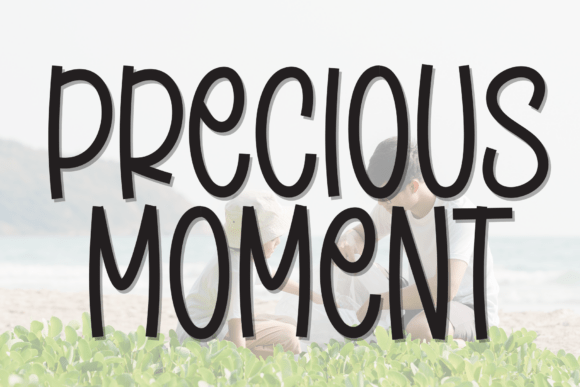
Precious Moment
قد يكون العثور على عناصر التصميم المناسبة أمرًا صعبًا، ولكن Precious Moment يقدم مجموعة استثنائية ترتقي بعملك على الفور.
سواء كنت تقوم بإنشاء منتجات الطباعة عند الطلب أو دعوات الزفاف أو رسومات وسائل التواصل الاجتماعي، فإن Precious Moment هو الخيار المثالي.